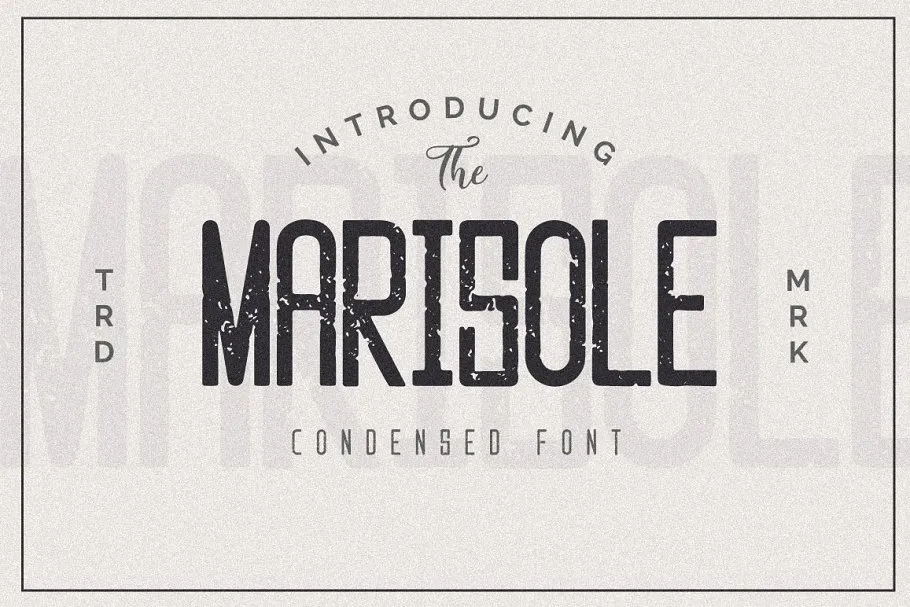
Marisole Typeface – Fonte Grátis
Marisole Typeface
A Marisole Typeface é uma tipografia para exibição com alta contraste, perfeita para todas as suas iniciativas de design. Suas características distintivas e sua textura rica dão-lhe um toque mais robusto e ousado, ideal para embalagens de whisky ou qualquer projeto que precise de força visual. Com Marisole Typeface, você terá uma fonte condensada de tipo abertamente texturizada, cada letra apresentando uma textura única e uma riqueza de cores fortes que contribuem para um tom atraente e sóbrio. Seja no tamanho grande ou no pequeno, esta fonte é perfeitamente adaptável às suas necessidades, tornando-a uma opção versátil para qualquer projeto design que você possa estar planejando.